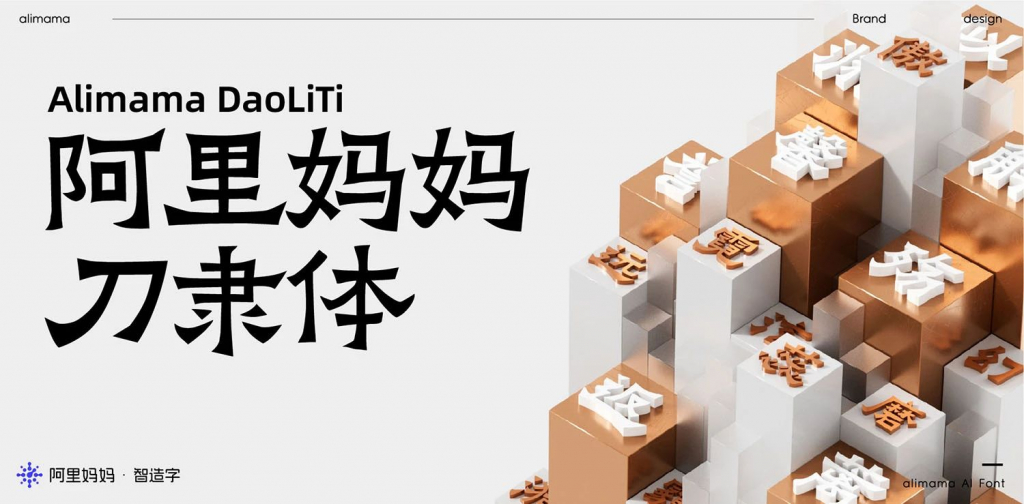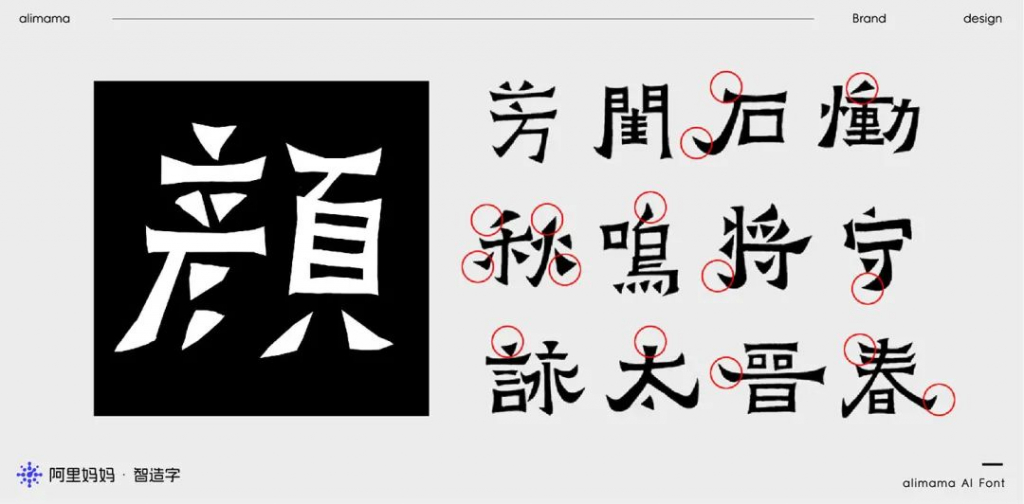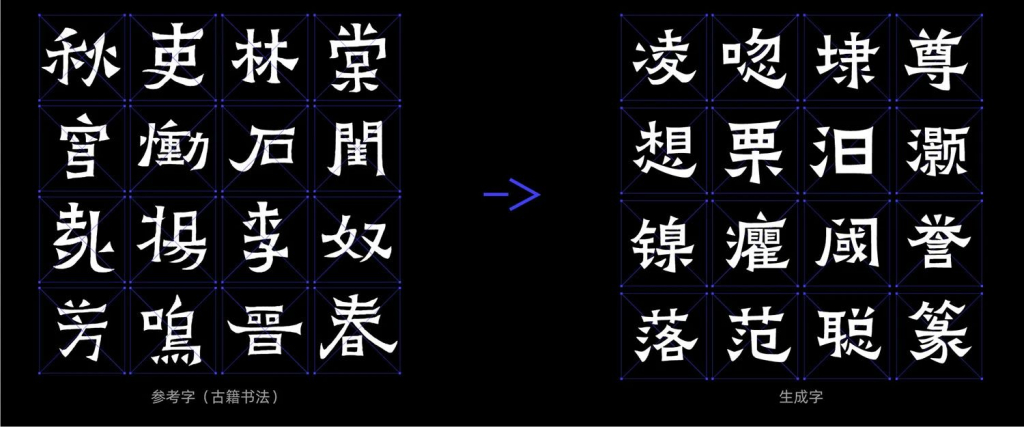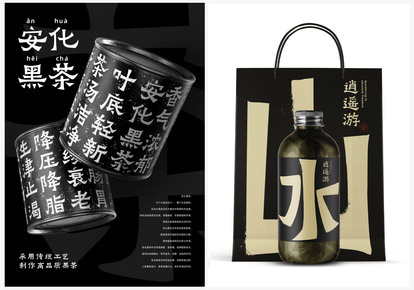
阿里妈妈刀隶体,通过机器学习了爨宝子碑的精髓,强调了三角点折弯与横画两端“雁尾”之方强,外露锋芒,耀其精神,介于隶楷之间,保持着浓重的隶书方笔意味,给人以坚实、朴茂、稚拙、倔犟之感,打破常规常态的匀称和均衡,结构极为大胆,布白和中宫常常出人意料,看似失度,实则深得艺理,险中求正,静中欲动,动中求静。
“阿里妈妈刀隶体”是一款书写很新颖的字体,字体大方,适合各种设计作品使用!欢迎下载!